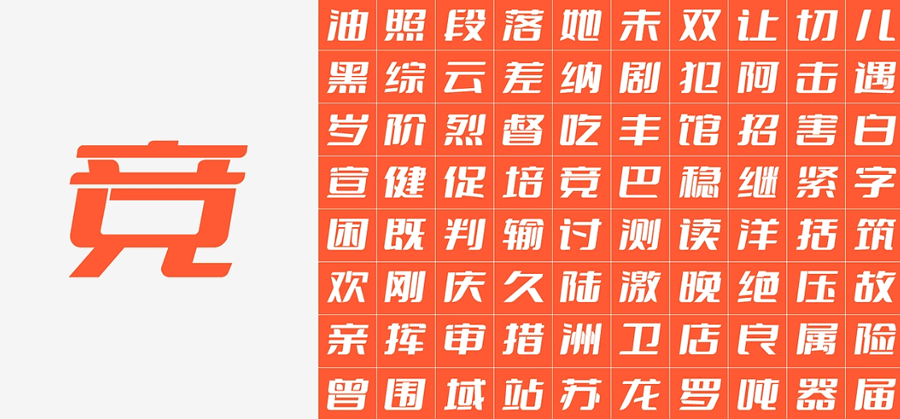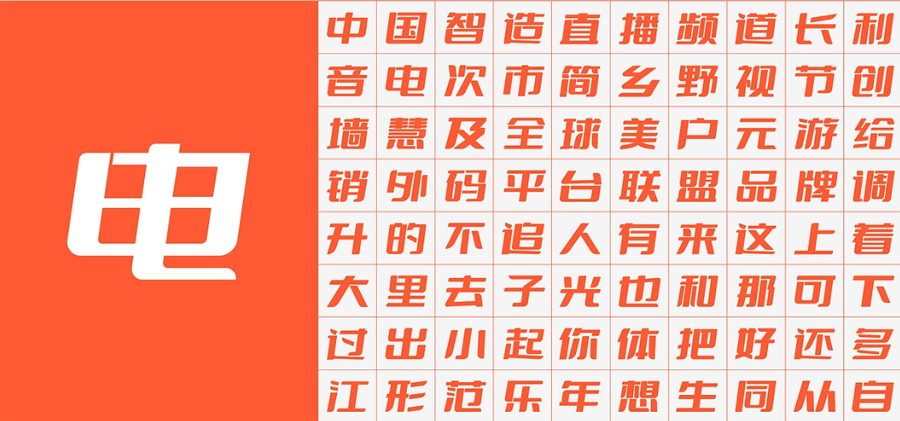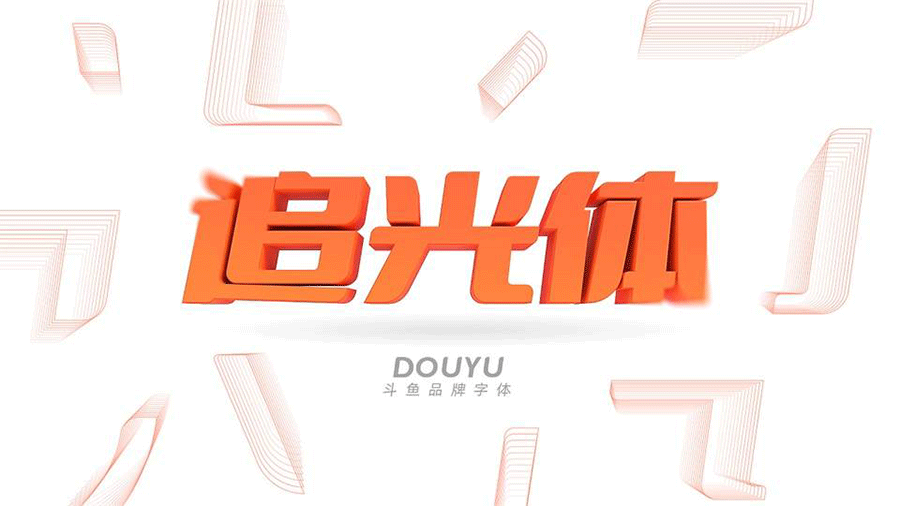
斗鱼追光体(DouYu Font)是由国内斗鱼直播平台于2021 年 7 月 21 日正式发布的一款品牌专属中文字体,由斗鱼武汉研发部 UED 提供指导,品牌组设计成员主导打造。
追光体延续斗鱼 LOGO 一贯的斜体风格,所有字符向右倾斜 8°,有一种向前冲的视觉效果,也体现了名字”追光”的寓意。字体结构横细竖粗,独特的鲨鱼鱼鳍式倒角设计让人眼前一亮。不管是网页标题、海报标题、视频标题还是游戏直播宣传物料、广告包装设计等都非常适用。
斗鱼追光体符合 GB2312 简体中文编码标准,包含 6763 个中文字符、100 个西文及数字符号,目前已推出了 2.0 版本,完全可以满足日常使用需求。且允许任何个人和企业免费使用,包括商用用途,但切记禁止用于商标注册或者违法用途。